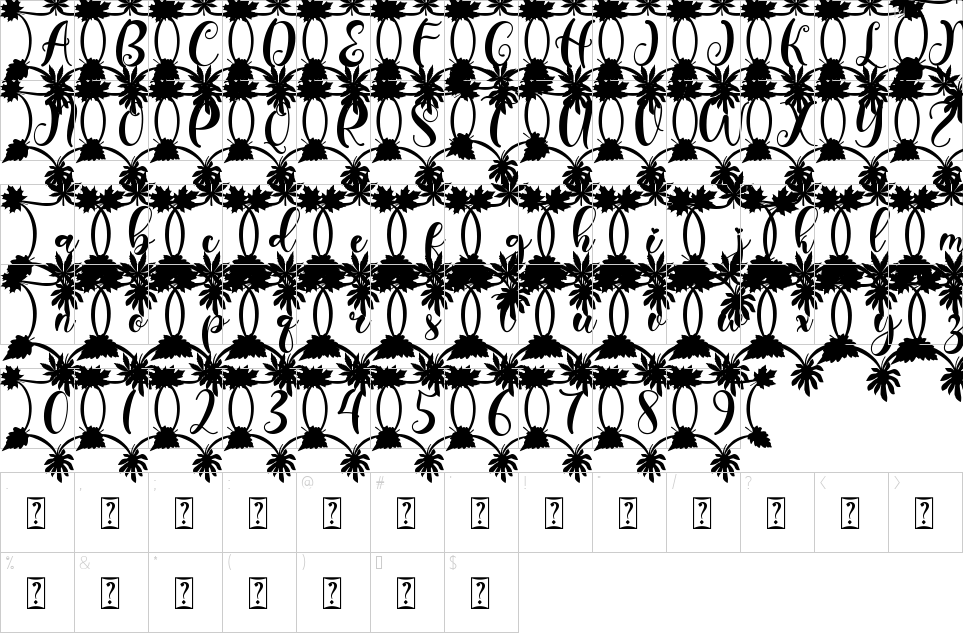
A fonte Dainty Autumn é uma elegante e atraente escolha para aqueles que buscam uma mão-dilhada para suas criações digitais no Windows ou Mac. Desenhada pelo designer Yoga Letter, ela oferece um toque delicado e suave capaz de tornar sua escrita mais amigável aos olhos do leitor. Com seu design agradável e versátil, Dainty Autumn é perfeito para textos em pequena escala ou quando você deseja dar um toque especial à sua marca online. Esta fonte foi baixada 131 vezes e continua a impressionar com seu charme e simplicidade, tornando-a uma opção inegavelmente convidativa para os designers digitais que valorizam uma combinação perfeita de beleza e praticidade.